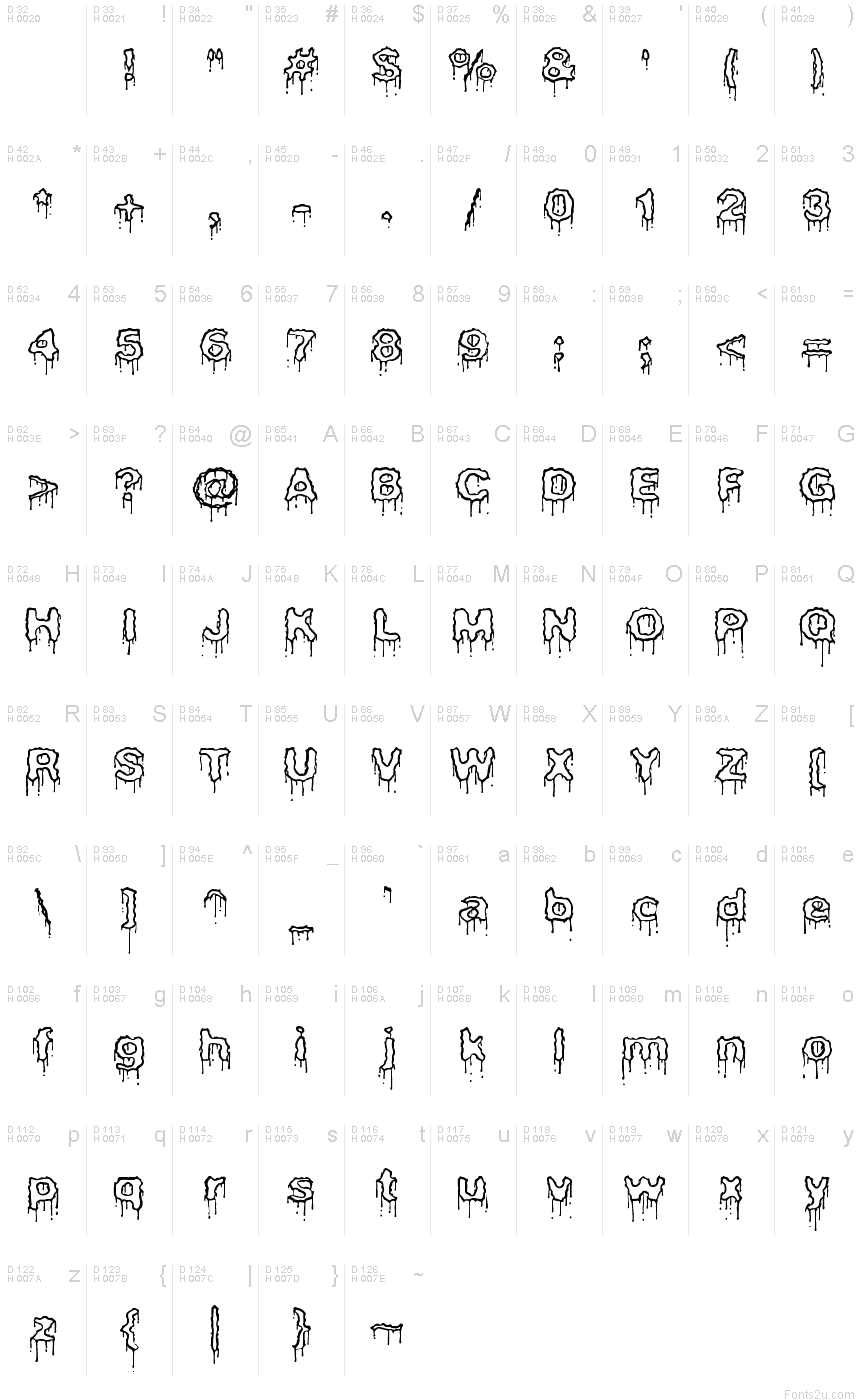
Plasma Drip Empty, di ÆNIGMA Fonts, è un carattere horror gratuito in stile outline, che richiama l'aspetto di slime, plasma o vernice fresca che cola lentamente lungo le lettere. Le forme sono bombate e irregolari, con un tratto tremolante disegnato a mano e lunghe gocce che conferiscono al carattere un mood da film di serie B, ben lontano dall'aspetto pulito di un fumetto.
Si adatta perfettamente a poster, volantini per Halloween, branding di attrazioni horror, artwork per musica underground e titoli camp, dove il contorno gocciolante fa quasi tutto il lavoro di ambientazione. Essendo un carattere gratuito, è ideale anche per nomi su packaging, copertine o intestazioni d'impatto che richiedono una silhouette vischiosa e instabile.